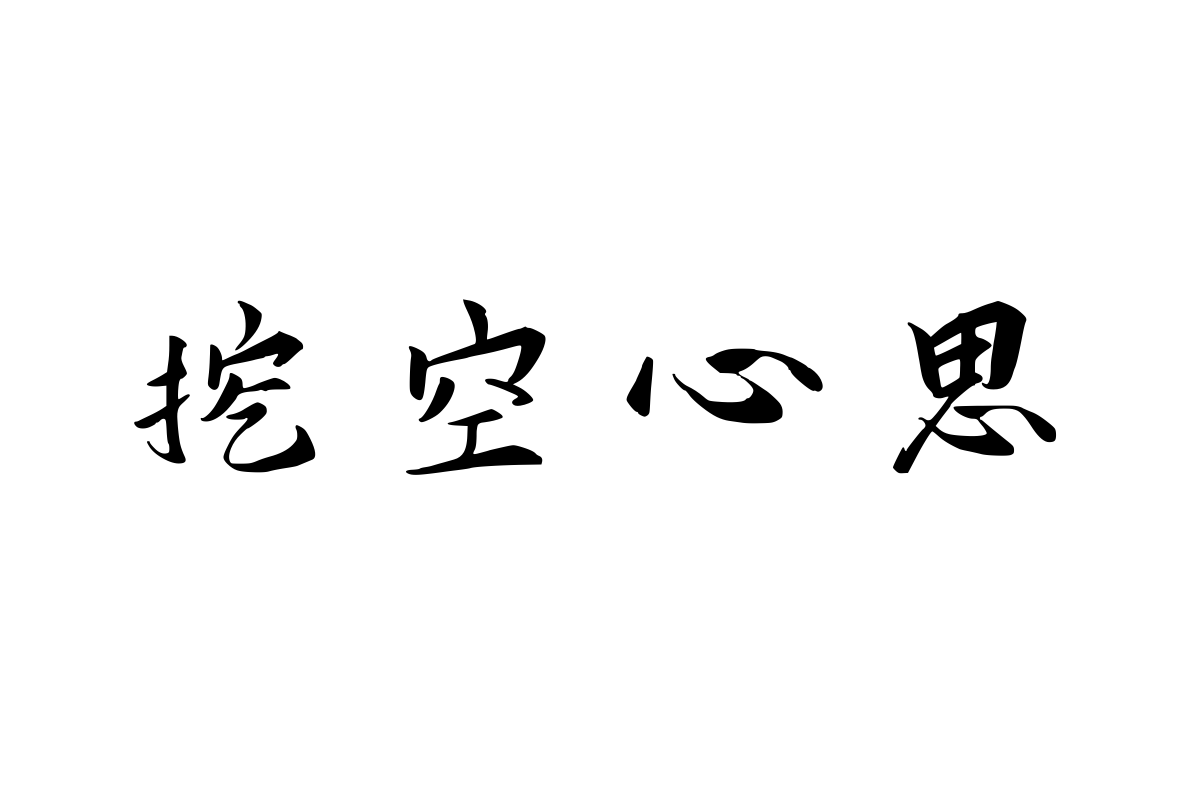
兰米泽阳行楷是一套由兰米泽阳创作的行楷字体,具有独特的风格和特点。该字体采用简洁、流畅的线条勾勒出汉字的基本结构,同时在笔画的连接处进行了适当的调整,使得整体看起来更加和谐自然。
兰米泽阳行楷的特点在于其对传统行楷字体的继承和发展。在保持行楷字体的基本特征的基础上,该字体更加注重线条的流畅性和美感,使得书写时更加轻松自如。同时,兰米泽阳行楷还注重对字形的规范和统一,使得整体看起来更加整齐划一。
总的来说,兰米泽阳行楷是一种既具有传统韵味又不失现代感的行楷字体,适合用于各种场合的文字书写,如书法作品、广告设计、网页设计等。